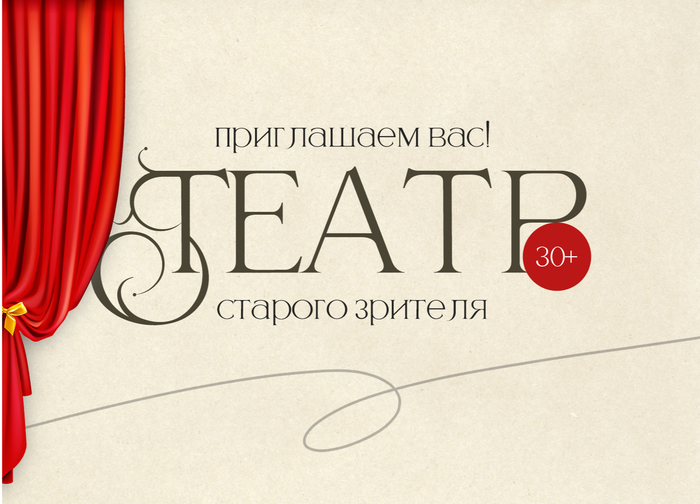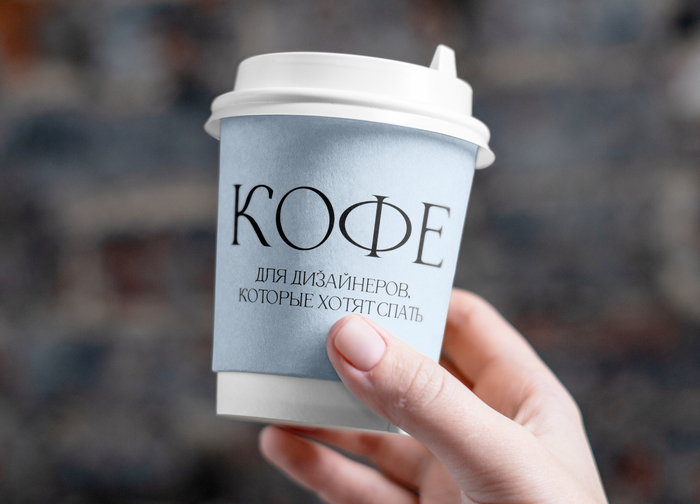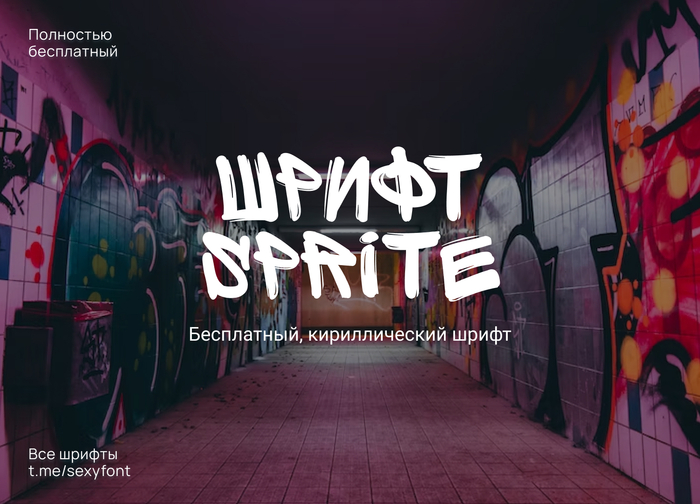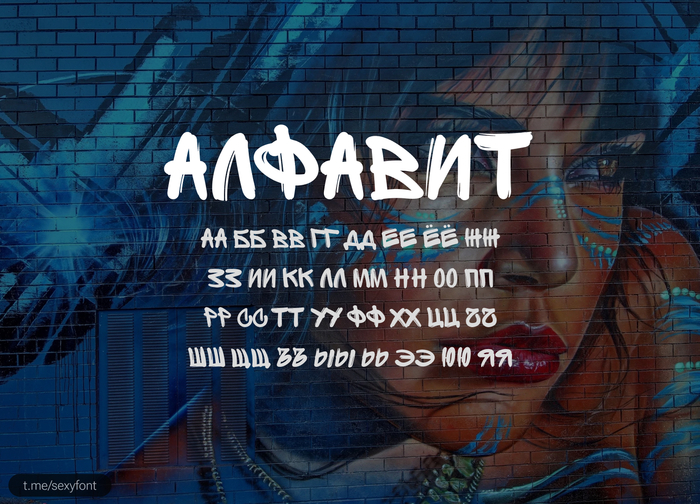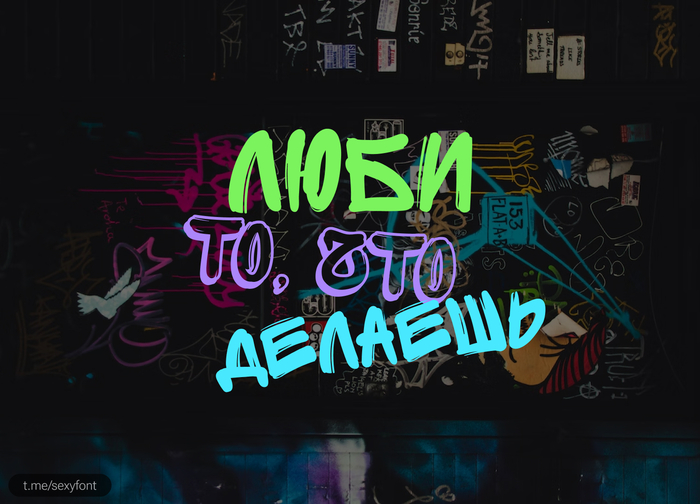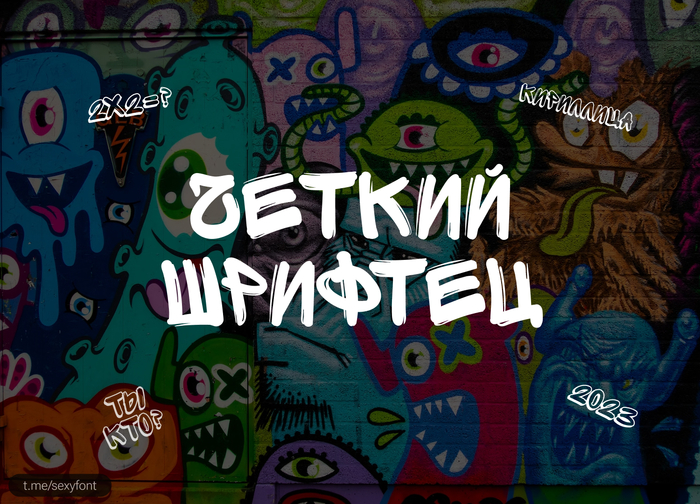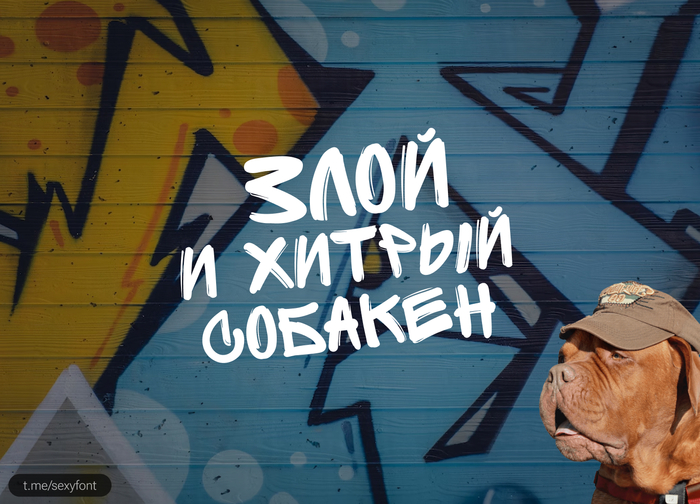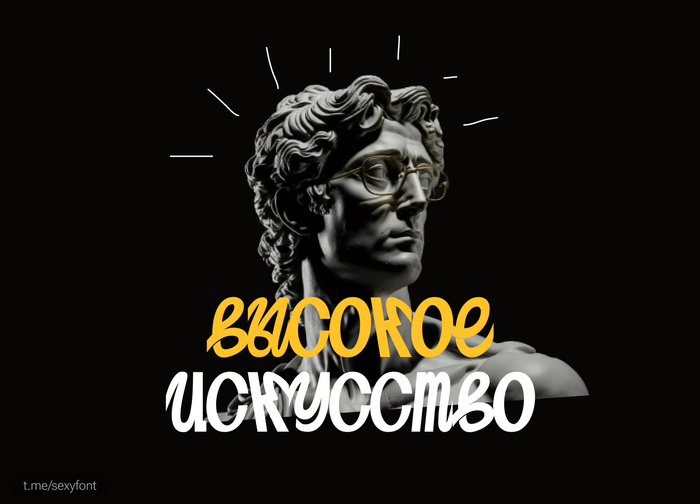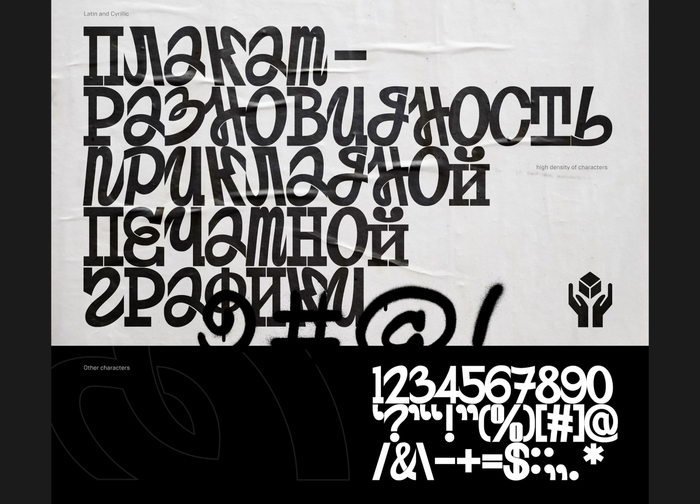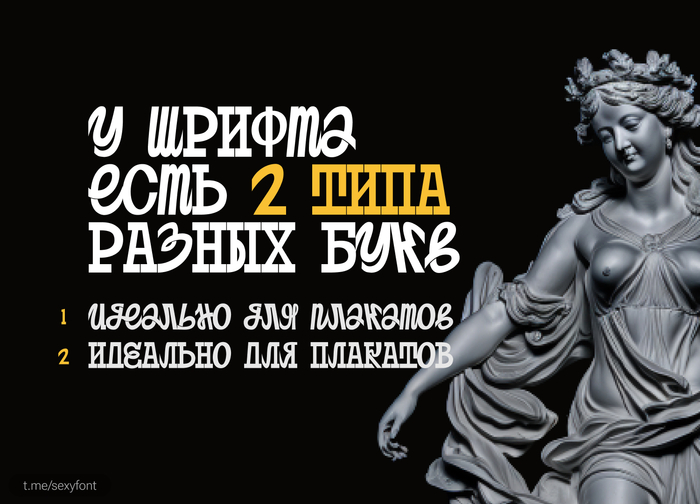
Кириллические шрифты
Красивый шрифт. Беролд. Кириллица
Роскошный шрифт с элегантными засечками. А название то такое. Berold. Что-то на бородато-бохатом. Отлично впишется в открытки, в постеры, в оформление сообществ. Бесплатно для личного использования. Судиться с вами сомневаюсь, кто будет) Автор с Индонезии. Автор: joko setiono. Презентация моя.
Шрифт в стиле граффити. Кириллица
Старенький шрифт, но определенно должен быть в коллекции каждого. Имитация граффити баллончиком. Автор: FourPlus Studio. Бесплатно для личного и коммерции.
Шрифт постер. Кириллица
Постерный шрифт. Акцидентный, поэтому читаемость не шик. Для коротких словечек самое оно. Но буквы выглядят очень необычно. По лицензии, написано бесплатно. Конкретно для личного или коммерции автор не указал.
Кириллический шрифт пирог
Безлимитный пирог. Так называется наш следующий шрифт) Веселый, озорной. Поддерживает кучу языков. Мой родной – башкирский. А так же казахский, французский, испанский и т.д Бесплатно для личного и коммерческого использования. Автор: Екатерина Бакирова
Шрифт бригантина. Бесплатная кириллица
От автора: Посвящается великому советскому детскому писателю Владиславу Крапивину. Он пропитан духом его книг, детской приключенческой романтики. У шрифта ярко выраженный «детский» характер, налёт ретро-романтичности. Может использоваться в айдентике, оформлении книг и журналов, фильма и мультфильмах.
Рекомендованный набор по умолчанию — набор строчными. Не рекомендовано использовать для набора больших массивов текста.
Шрифт в стиле кока-кола
Кириллический шрифт Vetrino
Шрифт Vetrino. Кириллический шрифт с засечками. Поддерживает татарские символы) Такое не супер часто встречается. Начертание бесплатно для личного и коммерции.
Шрифт в форме косточек. Кириллица
Костлявый шрифт для твоих проектов) Идеально под хорор тематики. Для декоративного шрифта он имеет хорошую читаемость) Автор: 2DFUNS. Текущее начертание бесплатно.